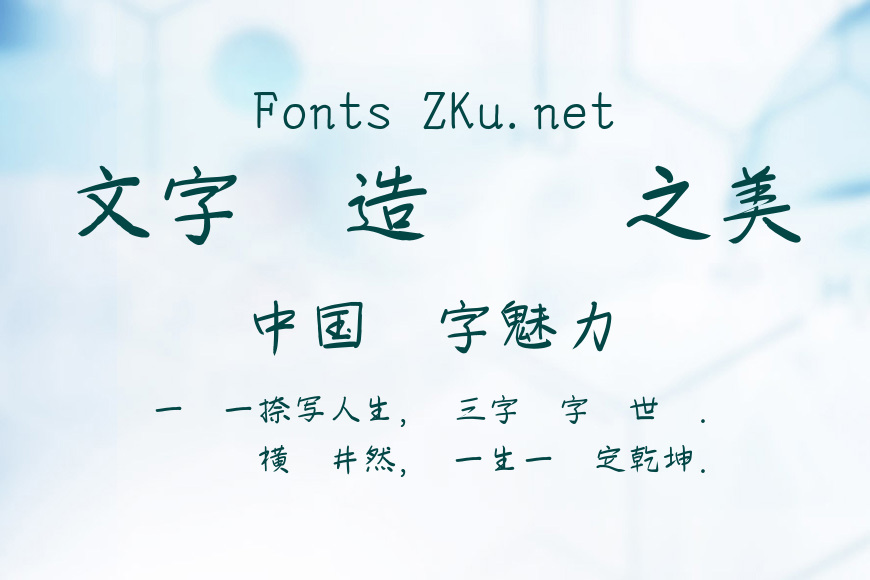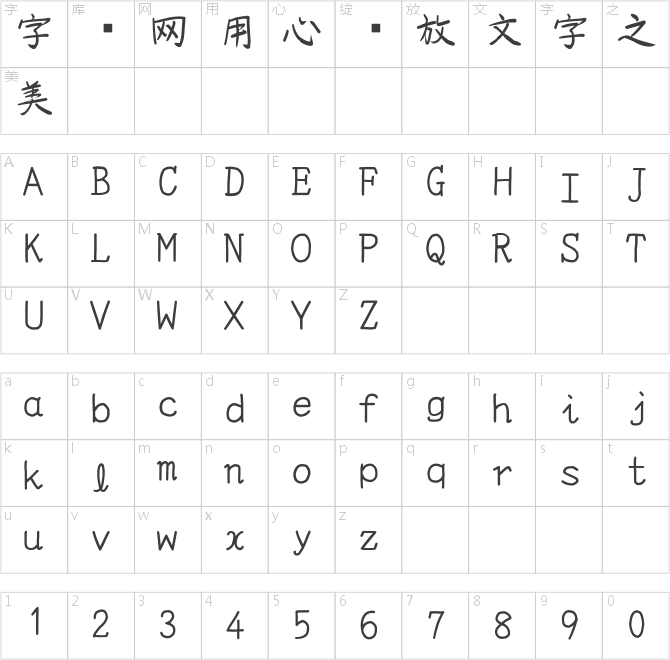
YOzFont鋼筆
YOzFont钢笔字体是手写风格的字形。这个字体笔画干净利落,笔触上带着手写的笔锋,看上去挺不错的。只可惜这是日本设计的制作的字体,对简体中文支持较差,对繁体支持很好。
YOzFont鋼筆字体YOzFontK钢笔字体字库是一款让人赏心悦目、百看不厌的日文字体,适合各类广告和产品包装设计应用,字体大小7.35MB,格式为TTC字体,上传用户是Pt.赵鹏涛,作者/版权方为Y.Oz